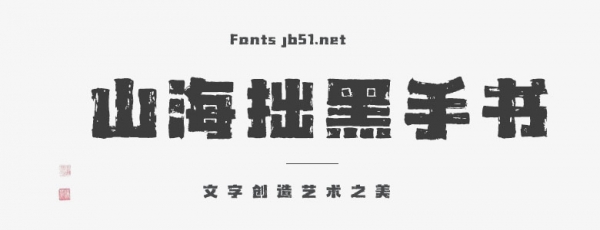
山海拙黑手書是一款全新的毛筆風字體,包含漢字9169個,符號200+個。該字體的毛筆筆鋒狂野有力,非常醒目!字形古樸渾厚,在渾厚的同時而又極富張力,桀驁不馴的特性,霸氣外露。它的筆畫充滿力量感,組合搭配極富強烈的節(jié)奏感。在粗細的縱橫間,擁有非常規(guī)的張力特性。筆畫的飛白效果使字體的氣息更加流暢,筆畫間的關系密不可分,同時也增加了字體的自由灑脫之感。